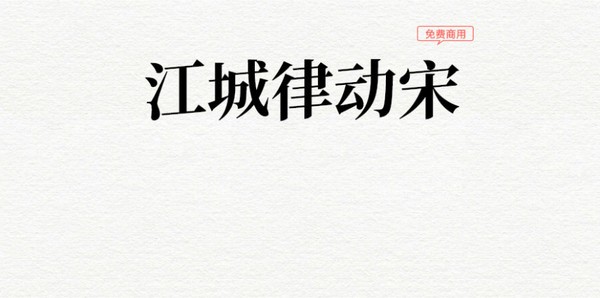
江城律動宋字體
江城律動宋字體介紹:
江城律動宋是大神@劉鵬基于思源宋體CN-Bold向上傾斜5度改造的一款字體。江城律動宋字體向上傾斜,上下律動,自帶活動促銷BGM,天生適用于活動、促銷等廣告語,適當(dāng)縮小字間距效果更佳哦。
江城律動宋體特點:
這款字體與貓啃網(wǎng)之前發(fā)布的@新愚公制作的貓啃網(wǎng)風(fēng)雅宋有點類似,@劉鵬和@新愚公他們的想法創(chuàng)意都想到一塊了,就是把字體向上傾斜,讓字體有了一種動感。江城律動宋與貓啃網(wǎng)風(fēng)雅宋的不同之處在于,兩款字體向上傾斜的角度不一樣,江城律動宋的傾斜度會更高一點,而貓啃網(wǎng)風(fēng)雅宋就是微微一突很傾城。另外貓啃網(wǎng)風(fēng)雅宋對字體進行壓縮,感覺會修長一點,并且字體重心會也感覺更高了。同樣的字號,風(fēng)雅宋會字會更小一點。